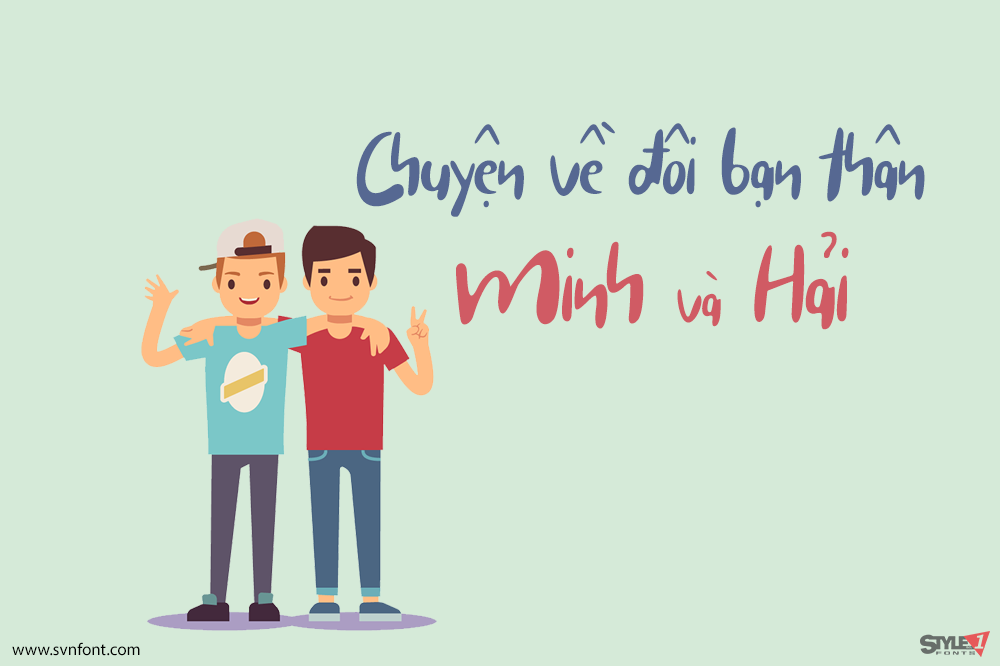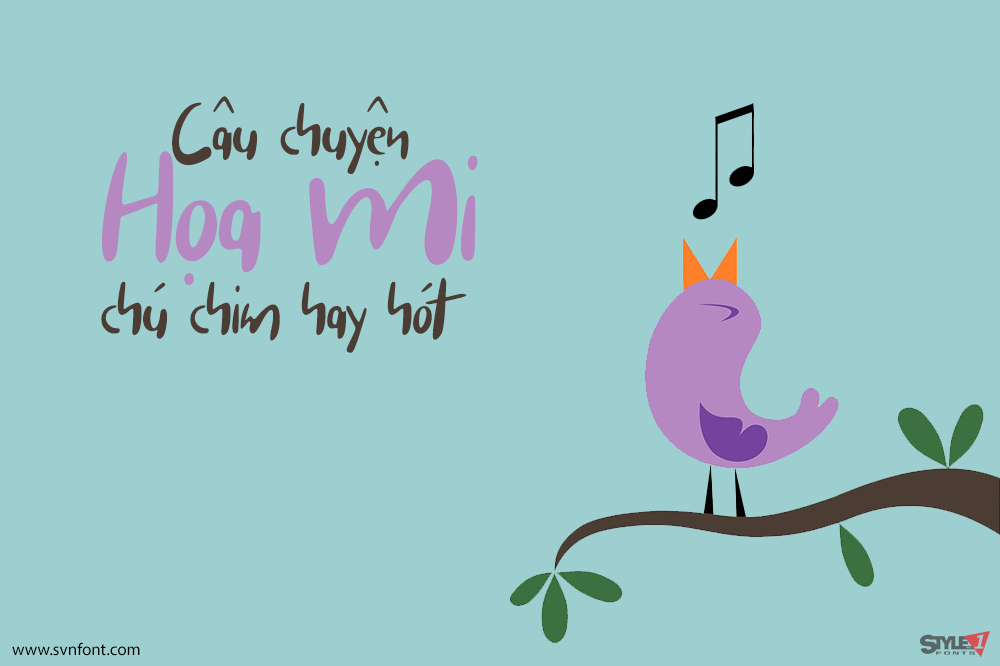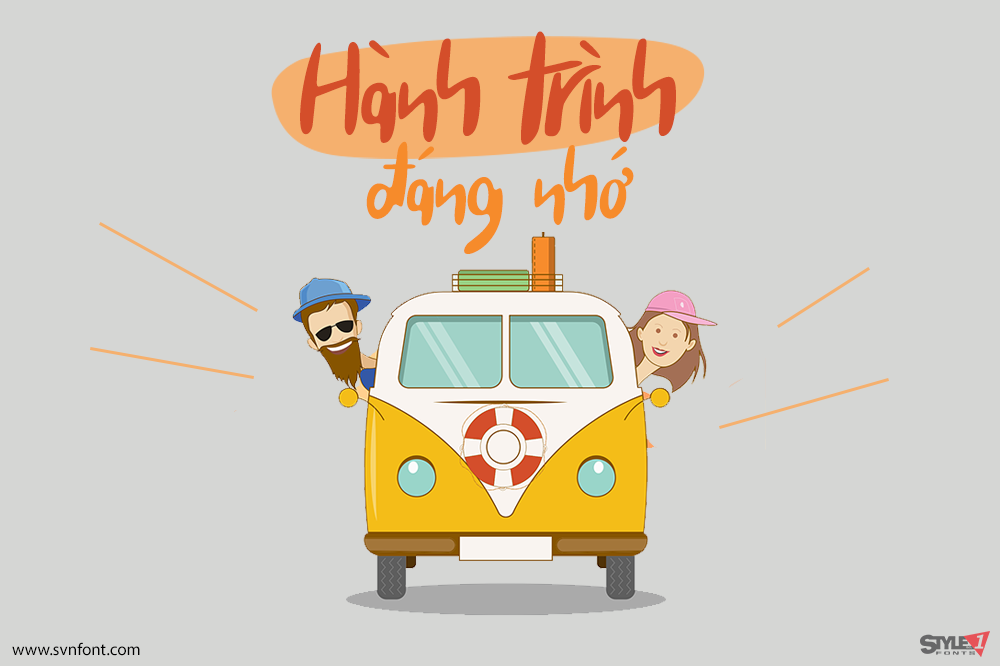
Carista là một font chữ display độc đáo và vui nhộn với nét tinh nghịch. Hãy sử dụng font này để thêm dấu ấn cá nhân cho bất kỳ thiết kế nào!
Nhà thiết kế: Zain Fahroni
Nhà phát hành: Fourlines studio